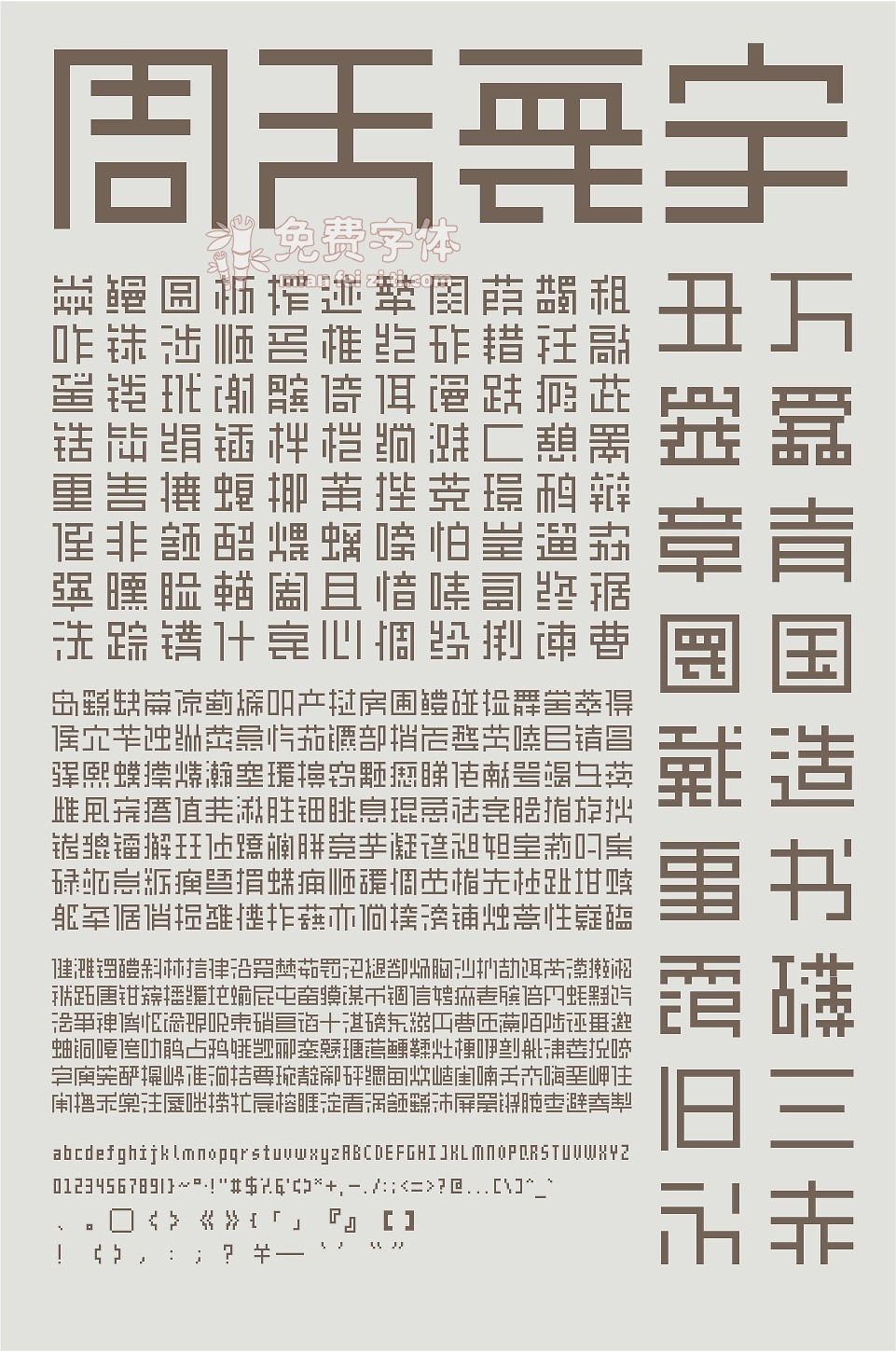
这是一款类像素体的字体。
与像素体相同之处为——1)以笔画宽度为基准,有最大尺寸限制(11X11);2)笔画由点与横竖线构成。
由于存在尺寸限制,对于复杂的字型必然是要简化的。其简化策略为:优先在保持部件外围结构的情况下简化部件的笔画(例:目→日→口),其次才会考虑改变复合部件的结构(例:吕→日)。
简化字型会导致字型辨识度降低(也可以说是错误字型),若是着实不能接受,请谨慎考虑是否使用。